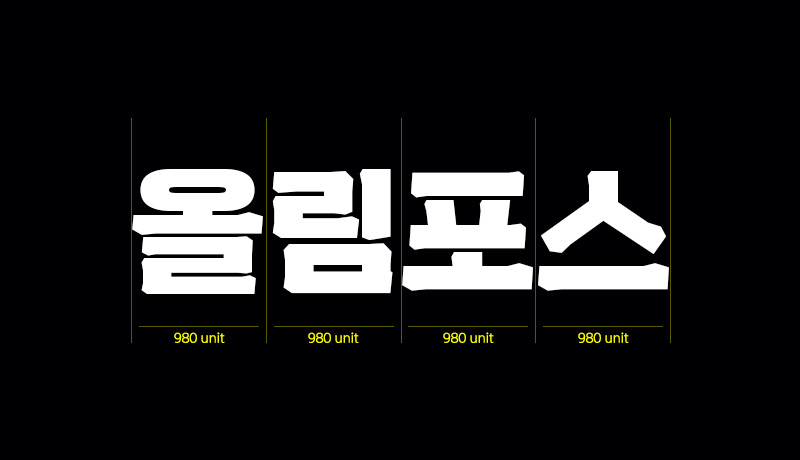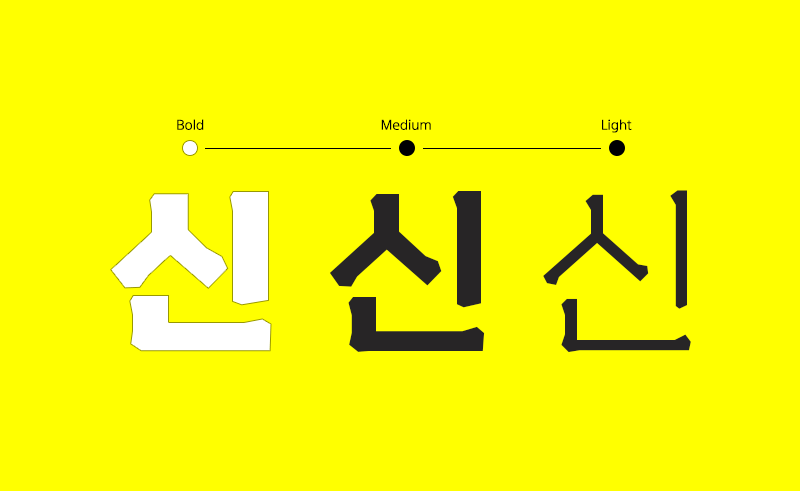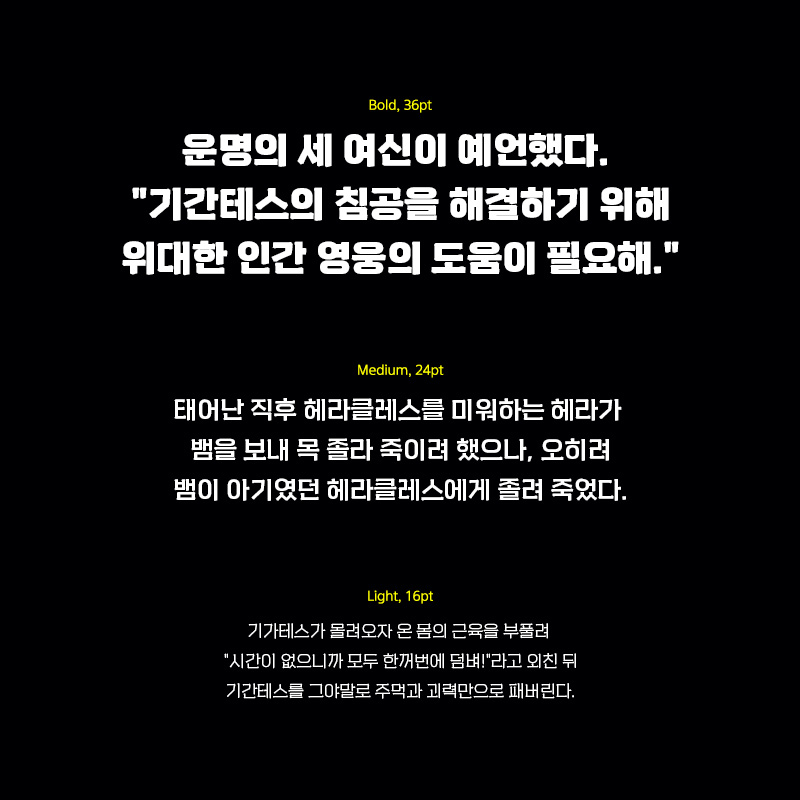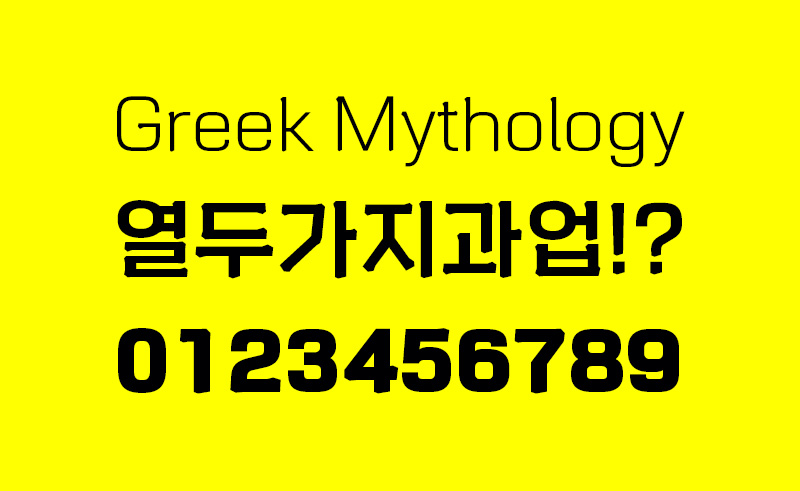
RixHercules
3 Style - Bold, Medium, Light그리스 로마 신화의 영웅들에게 영감을 받아 제작한 서체입니다.
단단한 뼈대와 투박하고 묵직한, 개성 있는 획이 특징으로 강인한 인상이 느껴집니다.
Light부터 Bold까지 3종의 웨이트로 다양한 분위기를 연출할 수 있습니다.
| FontFamily | Rix헤라클레스 / RixHercules |
| Design | Park Yong-rak, Choi Beop-Ho |
| Direction | Park Yong-rak |